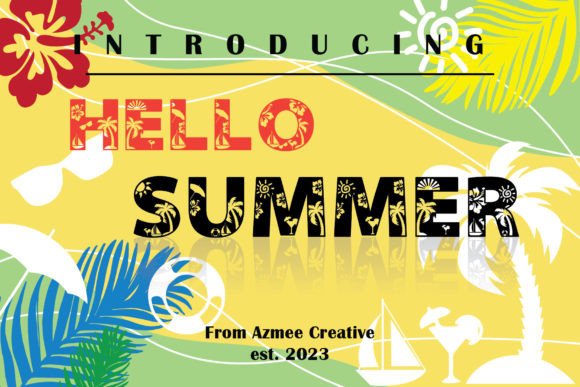
Hello Summer
Conçu avec précision, Hello Summer offre des vecteurs nets, une typographie fluide et une licence commerciale pour une tranquillité d'esprit.